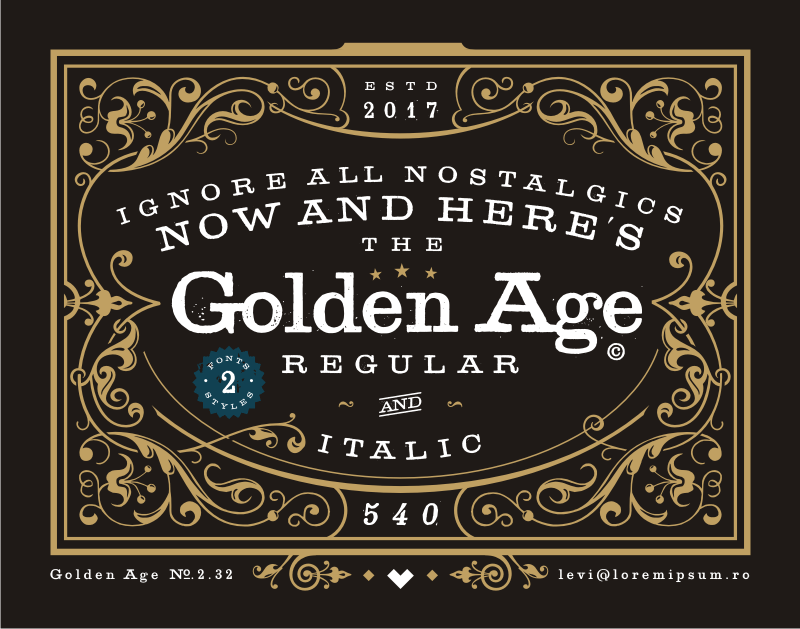
A Golden Age Typeface é uma fonte Slab Serif que transporta você para a elegância dos anos 30, restaurada de um original do século XX e adaptado com cuidado por Levi Szekes. Esta fonte mantém as formas e espaçamentos originais tão quanto possível, respeitando o estilo vintage sem tirar o foco dos detalhes essenciais. A versão itálica foi projetada para permitir a inclinação do texto de forma mais artesanal, uma vez que muitas antigas fontes perdiam esta característica ao longo do tempo. Um toque especial foi dado à hash e ao ampèreus (e) com os símbolos “Número” e “AND”, respectivamente, dando um tom refrescante de referências atuais a uma fonte de época. A Golden Age Typeface é perfeita para criar design gráfico que ressoa com o passado, ainda assim mantendo uma ligação concreta ao presente. Seu tamanho expansível e aparência robusta fazem dela um excelente candidato para projetos em marketing, design gráfico corporativo ou até mesmo para ilustrações em estilo vintage. Com as letras largas e gominhas da fonte Golden Age, você tem a capacidade de criar formas arredondadas e ícones de forma natural, dando vida à sua ideia. Incluindo mais catchwords e elementos gráficos específicos no futuro será uma ótima maneira de explorar ainda mais a extensão das possibilidades desta fonte.